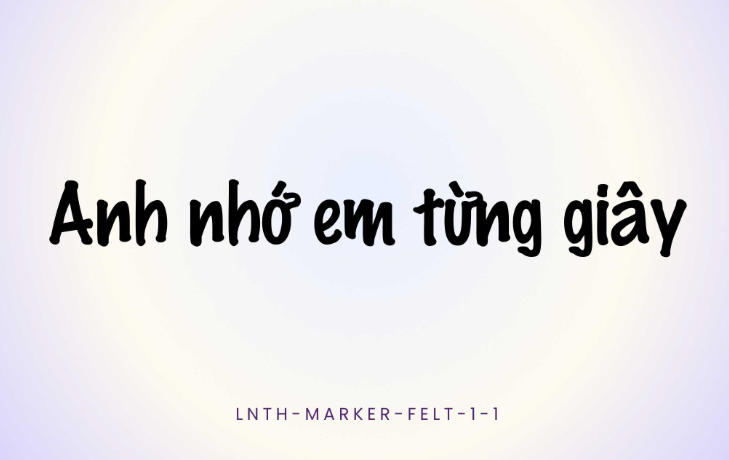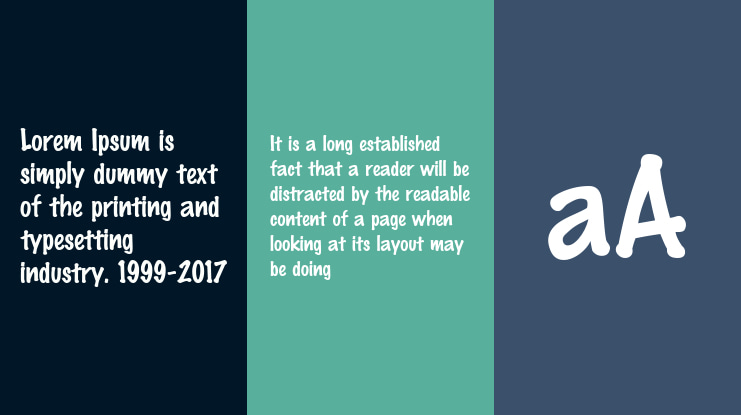
Marker Felt Font Việt hóa là bộ phông chữ thuộc dòng viết tay tự nhiên (Casual Script) mô phỏng chính xác những đường nét vẽ bằng bút dạ quang hoặc bút lông bảng ngòi tròn, mang lại cảm giác thân thiện, mộc mạc và tràn đầy sự sống động. Từng nổi tiếng toàn cầu khi xuất hiện trên ứng dụng ghi chú mặc định của hệ điều hành Apple, Marker Felt đã trở thành lựa chọn ưu tiên cho các thiết kế nhãn dán thực phẩm, bao bì tiệm bánh thủ công, menu quán cà phê và ấn phẩm thiếu nhi. Doozypack.vn cung cấp link tải font Marker Felt Việt hóa chuẩn kỹ thuật, giúp bạn sở hữu phông chữ độc đáo này mà không lo gặp bất kỳ lỗi hiển thị dấu thanh nào khi thiết kế in ấn.
Đặc điểm thẩm mỹ độc đáo của bộ font Marker Felt
Marker Felt không đi theo sự nắn nót của thư pháp hay sự khô cứng của các phông chữ hình học; nó chinh phục người xem nhờ sự ngẫu hứng chân thực của một nét chữ viết tay hàng ngày.
Phong cách bút dạ bảng (Felt-tip Marker) gần gũi và mộc mạc
Đặc trưng lớn nhất của Marker Felt Font Việt hóa là các đường nét có độ dày đều đặn với các góc chuyển hướng và đầu nét được bo tròn tự nhiên. Cấu trúc chữ mô phỏng áp lực mực bút dạ ngấm đều trên mặt giấy thô, tạo nên cảm giác ấm áp, thân mật và không chút kiểu cách. Khi đặt phông chữ này làm tiêu đề trên bao bì, thương hiệu của bạn sẽ ngay lập tức tạo được thiện cảm, giúp sản phẩm trông như được chăm sóc và chế biến thủ công bằng tất cả sự tận tụy.
Cấu trúc chữ bo tròn đầy đặn và dễ đọc
Dù mang phong cách viết tay tự do, Marker Felt vẫn duy trì được độ rõ ràng tuyệt vời nhờ tỷ lệ chữ cân đối cùng các khoảng hở trong chữ (counter) tương đối rộng rãi. Điều này giúp các dòng thông điệp, tên món ăn hay giá tiền trên bao bì hiển thị rõ nét, giúp người tiêu dùng dễ dàng tiếp nhận thông tin chỉ trong vài giây quan sát lướt qua trên kệ hàng.
Ưu điểm nổi bật của bản Marker Felt Font Việt hóa
Khi ứng dụng các phông chữ viết tay phổ biến vào thị trường trong nước, sự chỉn chu về dấu câu là yếu tố quyết định đến tính chuyên nghiệp của ấn phẩm:
- Khắc phục triệt để lỗi dấu tiếng Việt: Phiên bản Việt hóa đã được đội ngũ thiết kế trau chuốt thủ công từng dấu câu. Các dấu sắc, huyền, hỏi, ngã, nặng được vẽ với độ đậm và góc bo tròn hoàn toàn ăn khớp cùng thân chữ gốc, không gây cảm giác chắp vá hay làm méo mó bố cục chữ cái.